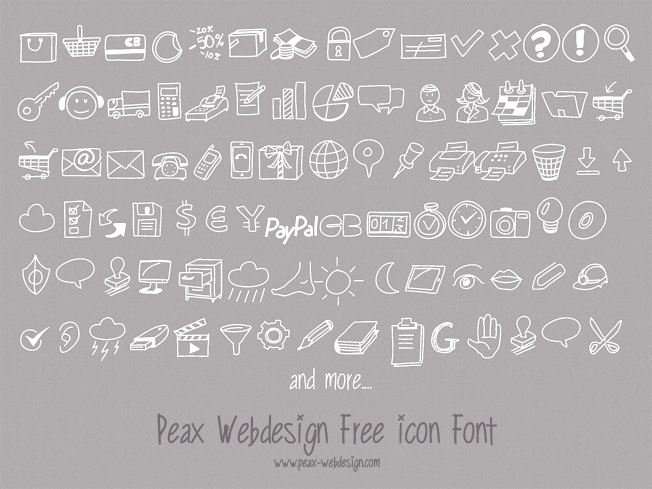
Typo d'icônes dessinées gratuite .ttf | Free sketched icon font
Création d'un nouveau pack d'icônes dessinées à la main : PW drawn icons.
Cette typo d'icônes couvrira largement tous les besoins, que ce soit pour un site Ecommerce, un site perso ou un blog.